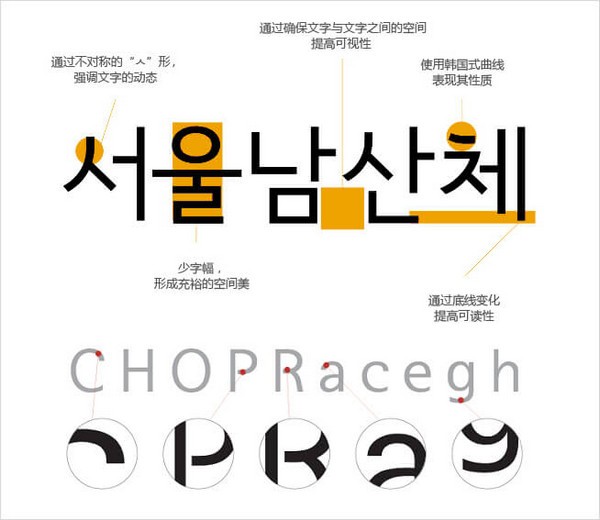
首爾市為廣泛使用首爾的固有字體,提升城市認同性與品牌價值而開發(fā)出明體系列的4種首爾漢江體(Light、Medium、Bold、Extra Bold)和哥特體系列的4種首爾南山體(Light、Medium、Bold、Extra Bold)、1種豎寫體等共9種首爾字體。
首爾字體中蘊含著強韌的儒生精神與端莊的余白美,從造型上展現(xiàn)了韓屋的開放和瓦片的曲線美。此外,首爾字體取名時采用首爾兩大代表性資源“漢江”和“南山”,更能激發(fā)市民對韓民族固有美麗語言——韓文的文化自豪感。